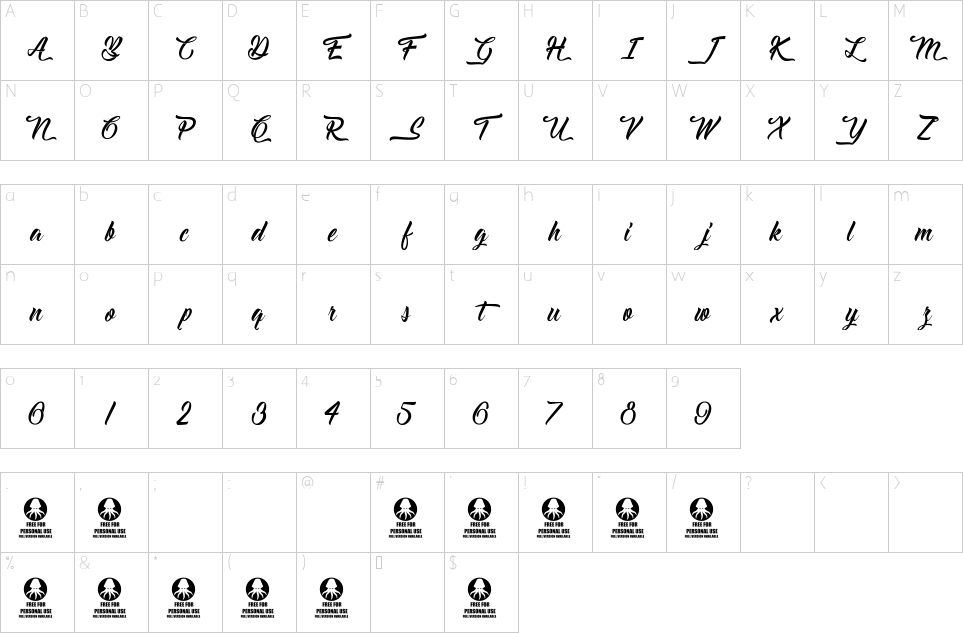
A Delightful Font é uma delícia para seus olhos e sua tela. Desenvolvida pela Octotype, esta elegante fonte é perfeita para qualquer projeto que deseje dar um toque divertido e alegre. Com 10.911 downloads no total, já provou sua utilidade e capacidade em tornar o texto mais agradável de ler. Seja em seu Windows ou Mac, esta fonte suave e charmosa se adequará perfeitamente aos seus projetos gráficos digitais. Descubra por si mesmo porque Delightful é uma ótima escolha para designers que desejam manter o design leve e agradável de suas páginas em um nível superior.